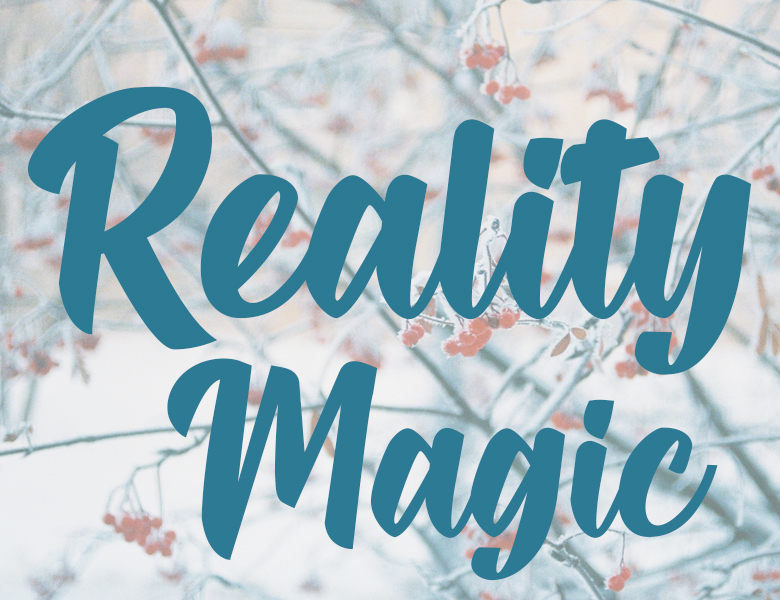
Reality Magic字体
简介:Reality Magic字体是一款设计精美的英文字体,该字体有很好的视觉感和充满时尚元素,流畅自如,整体效果大气,很有视觉冲击力。适用于广告设计、宣传海报、ppt方面的题材。该款字体风格:Regular;字符数:192;字形数:197;字体版本:Version 1.004;Fontself Maker 3.5.4。由站长素材提供免费下载,站长字体下载大全提供精选中英文字体素材。